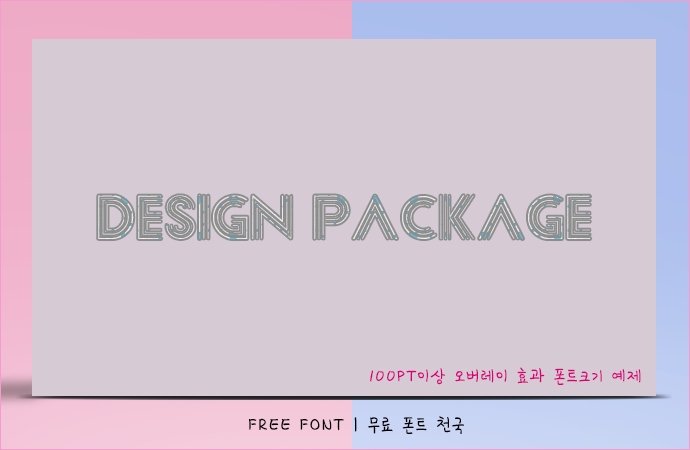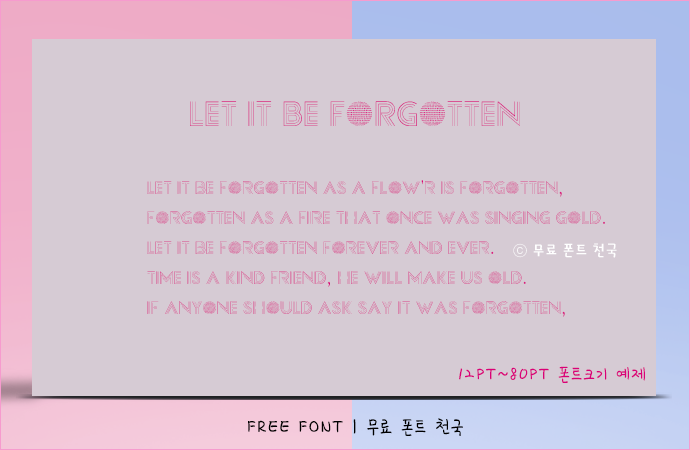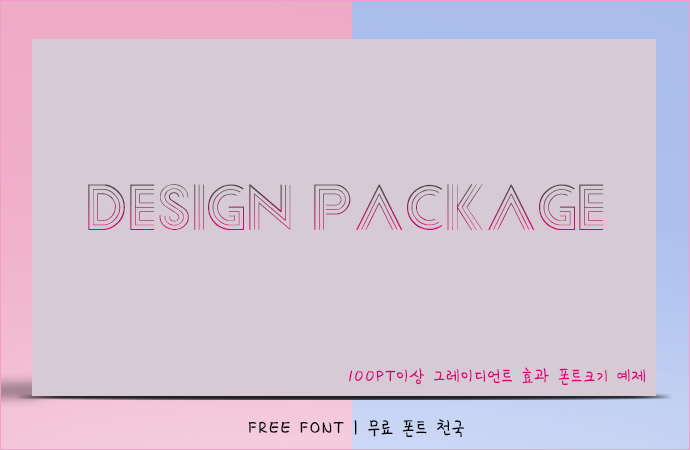
폰트에 라인 효과를 적용한 Confessions 영문폰트
서체에 독특한 라인 효과를 가미한 Confessions 영문폰트입니다. 오버레이 효과나 포토샵 상업용 필터로 사용되는 각종 필터 효과를 적용할 경우 매우 멋지게 표현되는 서체입니다.
Confessions 폰트 # 미리보기
Confessions 폰트, 12~80PT 크기로 적용한 효과
Confessions 폰트, 100PT 크기 이상으로 작업한 오버레이 효과
Confessions 폰트, 100PT 크기 이상으로 작업한 그레이언트 효과